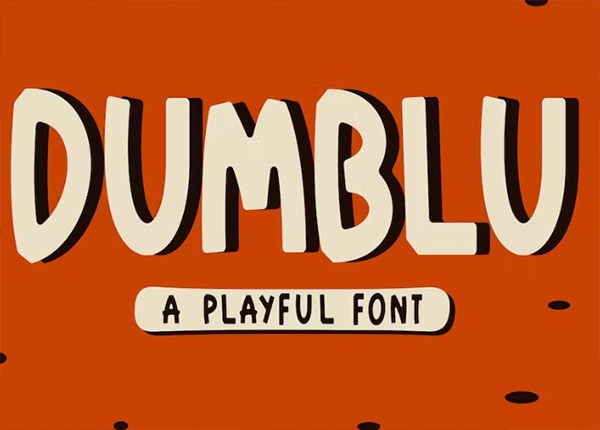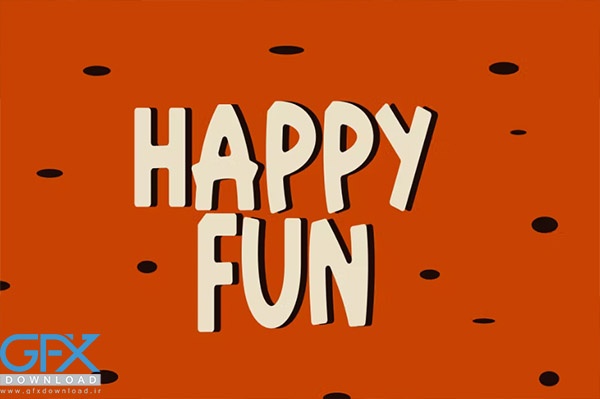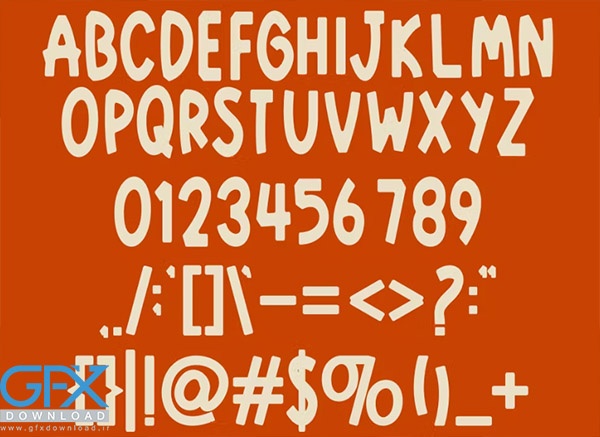
دانلود فونت فانتزی Dumblu
دانلود فونت بامزه Dumblu
دانلود فونت انگلیسی بامزه و فانتزی Dumblu
در این پست به معرفی فونت جدید با نام فونت Dumblu با شما همراه هستیم. فونت مدرن Serif که ظاهری زیبا، شیک و مدرن دارد. این فونت برای پروژه‌های مختلف مانند امضا، لوازم التحریر، لوگو، عروسی، نقل قول‌های تایپوگرافی، جلد مجله یا کتاب، سربرگ وب‌سایت، لباس، برندسازی، طراحی بسته‌بندی و غیره کاملاً مناسب است. برای دانلود فونت فانتزی Dumblu از جی اف ایکس دانلود با لینک مستقیم به ادامه مطلب مراجعه کنید.
فونت انگلیسی فانتزی Dumblu
فونت انگلیسی بامزه Dumblu
این فونت سرگرم کننده و بامزه مناسب کودکان، طراحی های فانتزی و همچنین، برندسازی مرتبط با مد یا طراحی سرمقاله و ... می باشد.
• نام فونت: Dumblu
• حروف بزرگ